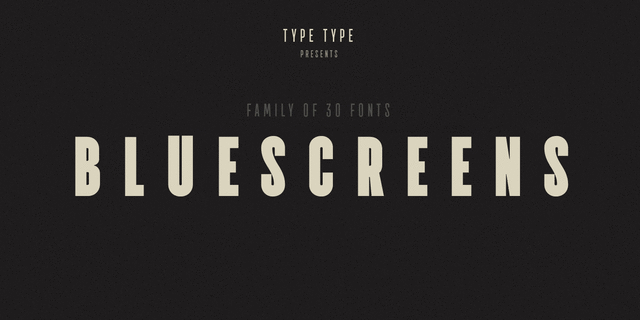
Bluescreens – гарнитура высокого качества, разработанная специально для киноманов и режиссеров. Это сжатый шрифт, включающий пять самых популярных насыщенностей: тонкий, светлый, нормальный, полужирный, жирный и их наклонные версии. Применяется в акцидентном наборе и отлично смотрится в логотипах, плакатах, титрах, заголовках. Разработан в студии TypeType в 2015 году.
ровный, стройный, худой, тонкий, легкий, сжатый, статичный, высокий, городской, монотонный, устойчивый, стабильный, точный, логичный, холодный, деликатный, невесомый, прозрачный, проволочный